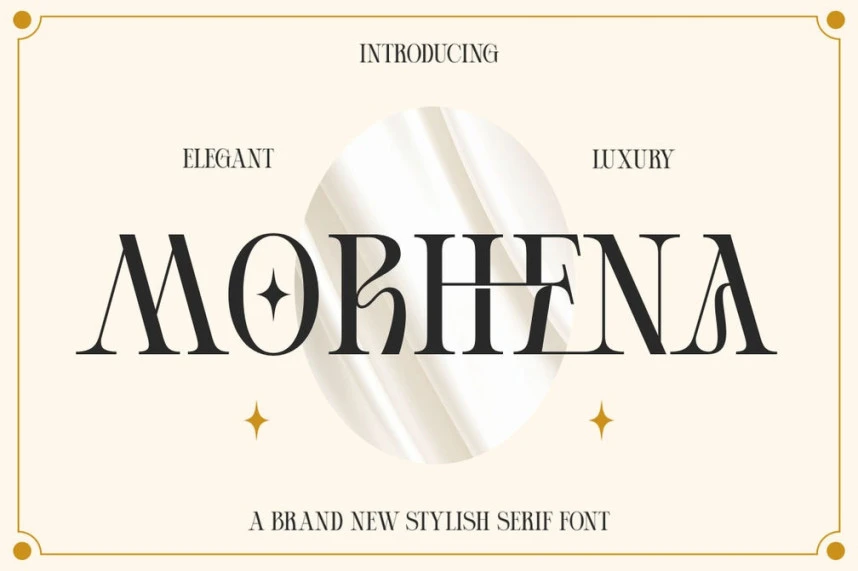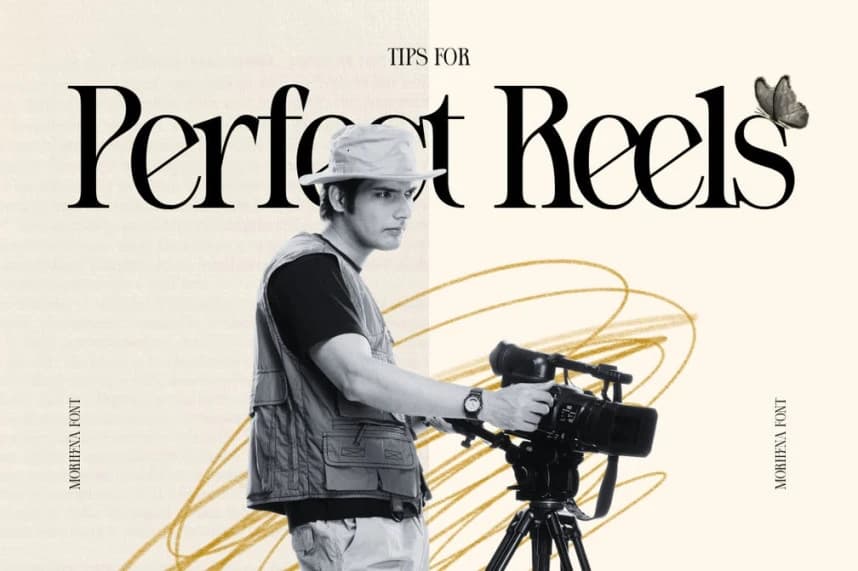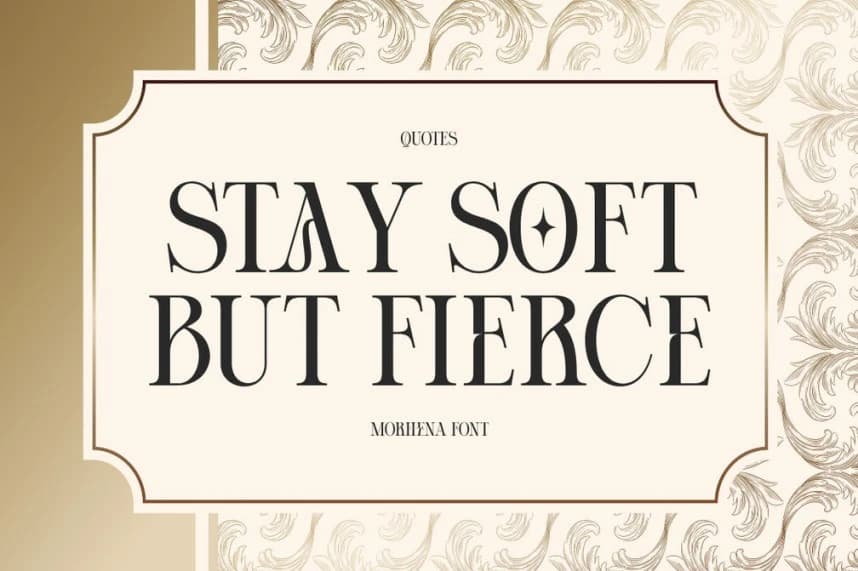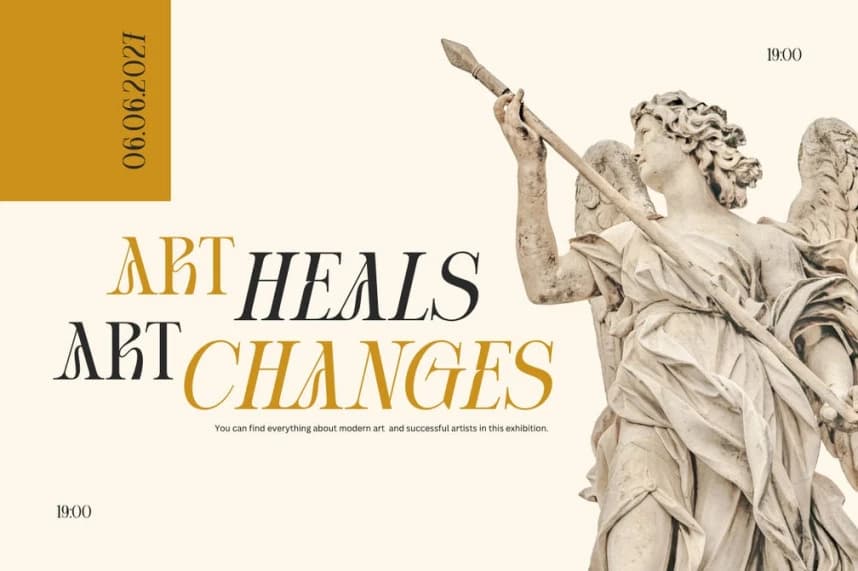
Morhena Font
Morhena Font, zarafet, prestij ve zamansız bir şıklığı ifade etmek için tasarlanmış lüks bir serif yazı tipidir. Özenli harf biçimleri, zarif eğriler ve yüksek kontrastlı detaylarıyla bu yazı tipi, premium markalaşma ve moda editoryalleri için mükemmeldir.
Morhena Font, zarafeti, prestiji ve zamansız bir sofistike görünüm ifade etmek için tasarlanmış lüks bir serif yazı tipidir. İnce yazı hatları, zarif kıvrımlar ve yüksek kontrastlı ayrıntılarıyla bu font, premium markalaşma ve moda editörlükleri için mükemmel bir tercihtir.